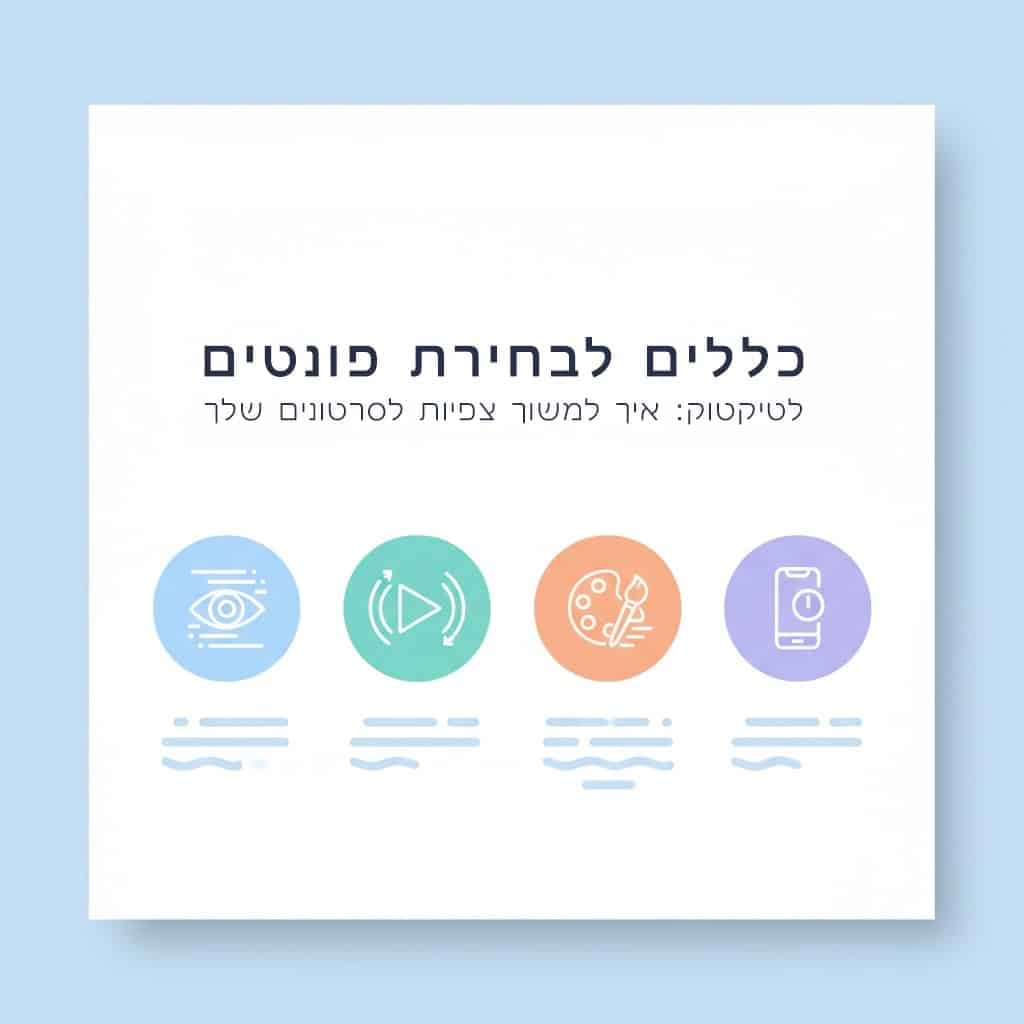
אם אי פעם גללתם בטיקטוק ועצרתם על סרטון רק בגלל הכתוביות המושכות שלו – אתם לא לבד. פונטים לטיקטוק הם אחד הכלים החזקים ביותר ליצירת תוכן שבולט, אבל רוב היוצרים לא מנצלים את הפוטנציאל המלא שלהם. הבעיה היא שהפונט הלא נכון יכול לגרום לצופים לגלול הלאה תוך שניות, בעוד שהפונט המתאים יכול להפוך סרטון רגיל לוויראלי.
הטיפוגרפיה בסרטונים קצרים היא לא רק עניין אסתטי – היא משפיעה ישירות על הקריאות, המסר והרגש שאתם מעבירים. בעידן שבו משתמשי טיקטוק צופים בתוכן בלי קול, הכתוביות הופכות למרכיב קריטי בהצלחת הסרטון. במדריך זה תלמדו איך לבחור ולהשתמש בפונטים שיעשו את ההבדל.
כשמדובר בתוכן ויזואלי מהיר, לפונט יש תפקיד כפול: הוא צריך למשוך תשומת לב תוך שבריר שנייה, ובו זמנית לאפשר קריאה קלה ומהירה. מחקרים בתחום UX מראים שמשתמשים מחליטים אם להמשיך לצפות בתוכן תוך 1.5-3 שניות הראשונות, והטיפוגרפיה היא אחד הגורמים המכריעים בהחלטה הזו.
יתרון נוסף של פונטים מעוצבים הוא יצירת זהות ויזואלית עקבית. כשאתם משתמשים באותו סגנון טיפוגרפי לאורך הסרטונים שלכם, הצופים מזהים את התוכן שלכם מיד – עוד לפני שהם קוראים את שם המשתמש. זה בדיוק מה שקורה עם יוצרי תוכן מובילים: יש להם "חתימה טיפוגרפית" שהופכת למותג מזוהה.
הפונט גם משדר רגש ואווירה. פונט אופטימיסט ה- sans-serif נקי ומודרני מתאים לתוכן טכנולוגי או מידעי. הבחירה הנכונה יוצרת התאמה בין המסר החזותי למסר המילולי.
לא כל פונט נולד לטיקטוק. הפלטפורמה דורשת קריטריונים ספציפיים שחשוב להכיר לפני שבוחרים טיפוגרפיה לסרטונים:
קריאות במסכים קטנים: רוב הצפייה בטיקטוק היא ממכשירים ניידים, כך שהפונט חייב להיות קריא גם בגדלים של 14-18 פיקסלים. פונטים עם קווים דקים מדי או פרטים מורכבים יאבדו את הבהירות שלהם. בדקו תמיד איך הפונט נראה על מסך הטלפון שלכם, לא רק על המחשב.
ניגודיות חזקה: הכתוביות צריכות להתבלט על רקעים משתנים ודינמיים. פונטים עם משקל bold או black מבטיחים שהטקסט יישאר קריא גם כשהסרטון מלא בתנועה וצבעים. אפשר גם להשתמש בשכבות צל או מתאר (outline) כדי להגביר את הניגודיות.
מהירות קריאה: צופים בטיקטוק רוצים לקלוט מידע במהירות. פונטים עם רווחים ברורים בין אותיות (kerning טוב) ומבנה פשוט מאפשרים קריאה של 3-5 מילים בשנייה. זה קריטי במיוחד לכתוביות שמלוות דיאלוגים או סיפורים מהירים.
התאמה לז'אנר: סרטוני קומדיה עשויים להרוויח מפונטים playful וקליליים, בעוד שתוכן חינוכי או עסקי זקוק לפונטים מקצועיים יותר. פונט הַלֵל עם האופי הסריף התנכ"י שלו יכול להתאים לתוכן תרבותי או היסטורי, ויוצר עומק ומשמעות.
עכשיו שאתם מבינים את העקרונות, הנה תהליך מעשי ליישום פונטים בסרטונים שלכם:
שלב 1: בחירת הפונט הראשי
התחילו בבחירת פונט אחד שייצג את המותג או הסגנון שלכם. זה יהיה הפונט שתשתמשו בו ב-80% מהכתוביות. חפשו פונט שמאזן בין אישיות לקריאות – משהו שמרגיש "שלכם" אבל לא על חשבון הבהירות. רכשו את הפונט עם רישיון אפליקציה כדי להשתמש בו בתוכנות עריכה ניידות.
שלב 2: הוספת פונט משלים
בחרו פונט שני שמשלים את הראשון למקרים מיוחדים – כותרות, הדגשות או קריאות לפעולה. אם הפונט הראשי שלכם הוא sans-serif נקי, הפונט המשלים יכול להיות פונט רוזטה עם הסגנון הגותי המעוטר שלו ליצירת ניגוד דרמטי. הכלל: לא יותר משני פונטים בסרטון אחד.
שלב 3: הגדרת פלטת צבעים
קבעו 2-3 צבעים עיקריים לטקסט שיתאימו למותג שלכם וייראו טוב על רקעים שונים. צבע אחד לטקסט רגיל, צבע שני להדגשות, וצבע שלישי אופציונלי לאלמנטים משניים. השתמשו בכלי בדיקת ניגודיות כדי לוודא שהצבעים קריאים על רקעים בהירים וכהים כאחד.
שלב 4: יצירת תבניות לשימוש חוזר
צרו 3-5 תבניות של כתוביות עם הפונטים והצבעים שבחרתם. שמרו אותן באפליקציית העריכה שלכם (CapCut, InShot, וכדומה) כדי שתוכלו להשתמש בהן שוב ושוב. זה חוסך זמן עצום ומבטיח עקביות ויזואלית לאורך כל התוכן שלכם.
גם יוצרי תוכן מנוסים נכשלים לפעמים בבחירת הפונטים. הנה הטעויות השכיחות ביותר:
שימוש בפונטים דקורטיביים מדי: פונטים עם קישוטים רבים, צללים מובנים או אפקטים מורכבים עלולים להיראות מרשימים בהתחלה, אבל הם הורסים את הקריאות. בסרטון בן 15 שניות, הצופים לא מספיקים לפענח טקסט מסובך. שמרו את הפונטים הדקורטיביים לכותרת בלבד, לא לכל הכתוביות.
התעלמות מגודל הטקסט: טעות קלאסית היא להשתמש בטקסט קטן מדי. כתוביות צריכות להיות בגודל שתופס לפחות 5-7% מגובה המסך, אחרת הן נעלמות. בדקו את הסרטון על מכשירים שונים לפני פרסום – מה שנראה טוב על אייפד עשוי להיות בלתי קריא על אייפון קטן.
ערבוב יותר מדי סגנונות: שימוש ב-3-4 פונטים שונים באותו סרטון יוצר תחושה כאוטית וחובבנית. הגבילו את עצמכם לשני פונטים מקסימום, ושמרו על היררכיה ברורה – פונט אחד לכותרות, פונט שני לגוף הטקסט. עקביות היא המפתח למראה מקצועי.
צבעים שלא תואמים את הרקע: טקסט לבן על רקע בהיר או טקסט כהה על רקע כהה הם מתכון לאסון. תמיד הוסיפו שכבת רקע מעט שקופה מאחורי הטקסט, או השתמשו במתאר (stroke) בצבע מנוגד. זה מבטיח שהכתוביות יישארו קריאות גם כשהסרטון עובר בין סצנות שונות.
רוב אפליקציות העריכה הפופולריות כמו CapCut או InShot מאפשרות ייבוא פונטים חיצוניים. אחרי שרכשתם פונט עם רישיון אפליקציה, הורידו את קובץ ה-TTF או OTF למכשיר שלכם. באפליקציה, חפשו את האופציה "Custom Font" או "Import Font" בתפריט הטקסט, ובחרו את הקובץ שהורדתם. הפונט יישמר באפליקציה לשימוש עתידי בכל הפרויקטים שלכם.
כן, יש הבדלים משמעותיים. טיקטוק מתמקד בסרטונים קצרים ומהירים, כך שהפונטים צריכים להיות קריאים מיד ובולטים יותר. באינסטגרם Stories יש זמן צפייה קצר אבל פחות תנועה ברקע, ואילו ביוטיוב הסרטונים ארוכים יותר ואפשר להרשות לעצמכם פונטים עדינים יותר. לטיקטוק תמיד בחרו בפונטים עם משקל bold לפחות וניגודיות גבוהה.
זכרו: הצופים בטיקטוק מחליטים תוך שניות ספורות אם להמשיך לצפות או לגלול הלאה. פונטים נכונים מושכים את העין, מעבירים את המסר במהירות ויוצרים זיכרון מותג. השקיעו זמן בבחירת הפונטים שלכם, והם ישקיעו בהצלחת הסרטונים שלכם.